Font viết tay Việt hóa đẹp tháng 3/2025
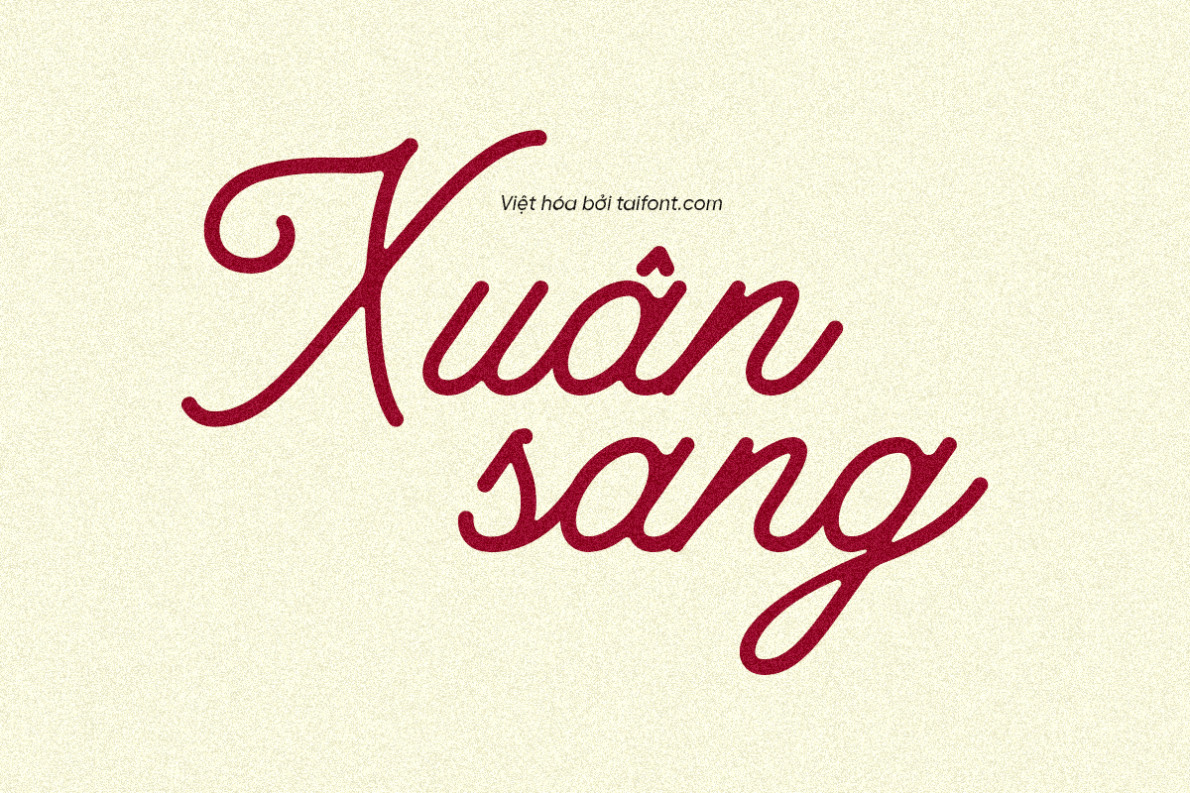
Giới thiệu bộ sưu tập Font viết tay việt hóa đẹp tháng 3/2025
Xin chào bạn đọc, trong tháng 3/2025, chúng tôi xin giới thiệu đến bạn bộ sưu tập các font viết tay việt hóa đẹp, phù hợp với nhiều loại thiết kế khác nhau. Dưới đây là những font tiêu biểu:
1. Font Palkofet
Với nét mảnh nhẹ nhàng, Palkofet là sự lựa chọn hoàn hảo cho các thiết kế thiệp cưới và logo chữ ký. Font này không chỉ mang lại sức hấp dẫn, mà còn thể hiện được sự tinh tế trong từng chi tiết.
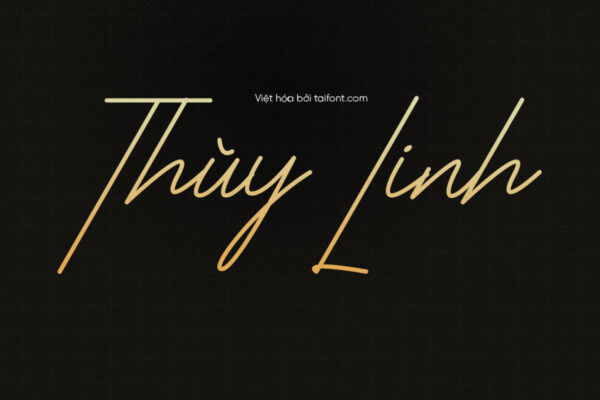
2. Font Jinglers
Jinglers mang dáng vẻ cổ điển, rất phù hợp với các thiết kế nghệ thuật. Sự kết hợp giữa nét viết tay tự nhiên và phong cách vintage khiến font này trở thành lựa chọn lý tưởng cho các sản phẩm thủ công mỹ nghệ.
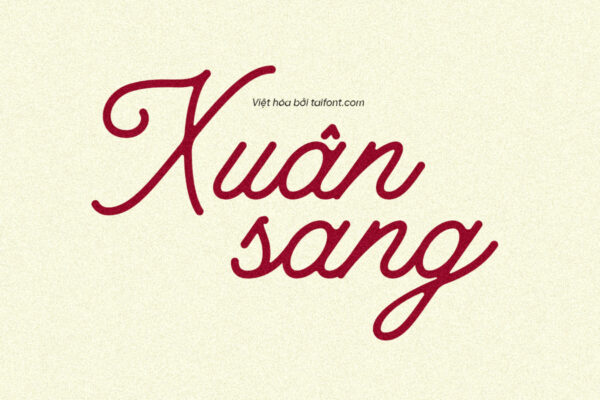
3. Font Amrack Signature
Amrack Signature mang đến vẻ tinh tế, nổi bật cho các thiết kế tiêu đề thiệp mời. Font này có thể làm bừng sáng mỗi lời mời, tạo nên sự hấp dẫn cho các buổi lễ trọng đại.
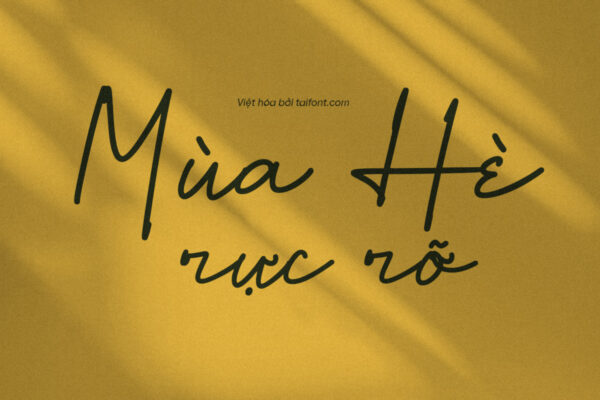
4. Font Budapest Bold
Đặc điểm nổi bật của Budapest Bold là nét đậm, giúp cho các tiêu đề thiết kế trở nên ấn tượng và thu hút sự chú ý. Đây là sự lựa chọn tuyệt vời cho những ai muốn tạo dấu ấn mạnh mẽ.
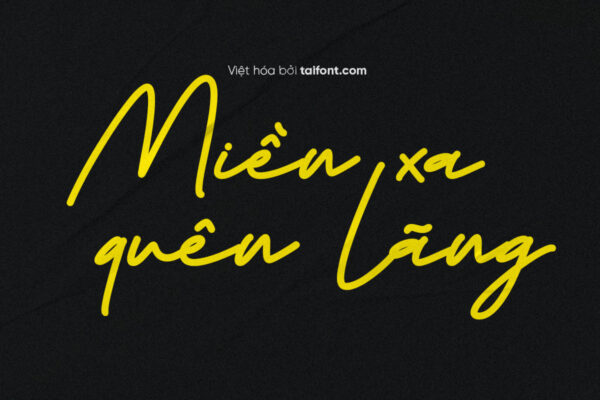
4. Font Budapest Regular
Với thiết kế thanh mảnh, Budapest Regular mang đến sự tự nhiên và sáng tạo. Font này phù hợp cho thiết kế thiệp cưới hiện đại, tạo cảm giác nhẹ nhàng, thanh thoát nhưng vẫn đầy cá tính.
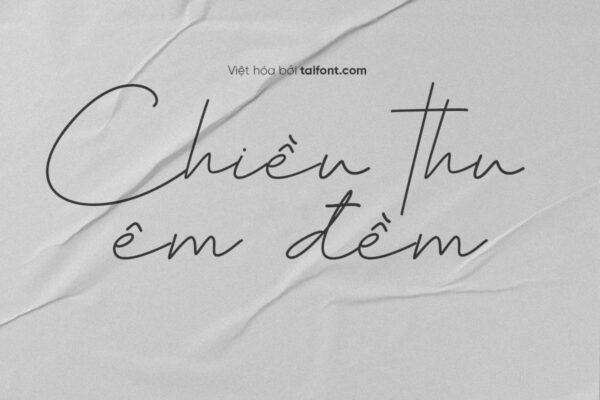
Hy vọng bộ sưu tập font viết tay việt hóa này sẽ giúp bạn có thêm nhiều lựa chọn thú vị cho các dự án thiết kế của mình trong tháng 3/2025!